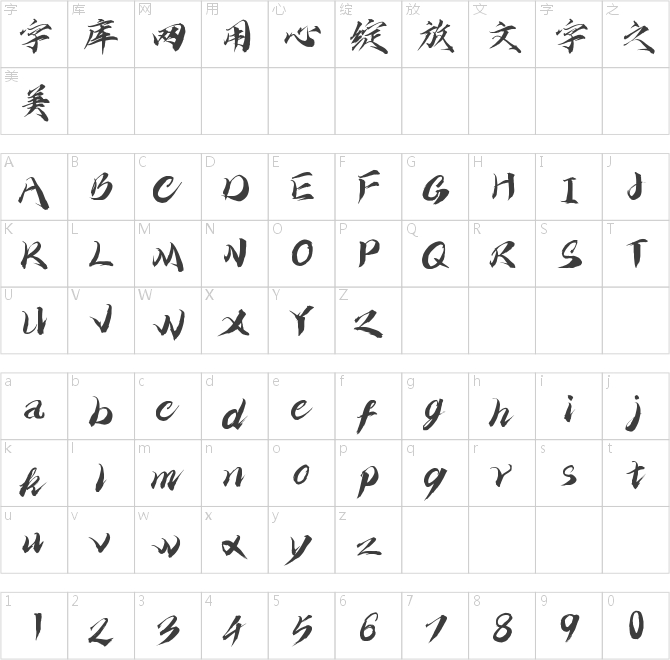
iSlide云猶體字體下載iSlide-YunYouTi
iSlide云猶體在秀麗毛筆字風格的基礎上更加強調了字體的曲折收放變化,使得整個字體開合揖讓有度,輾轉騰挪,不至過于秀氣婉約,婉轉中鏗鏘有力,鋒芒外露。
iSlide云猶體局部的形變與外拓帶來的是整體氣勢的疊加,兼顧了陰柔與陽剛、含蓄與強勁。露鋒用筆貫徹到了字體的始終,結體緊致,大量的曲線強化了字體的動感與字形張力。